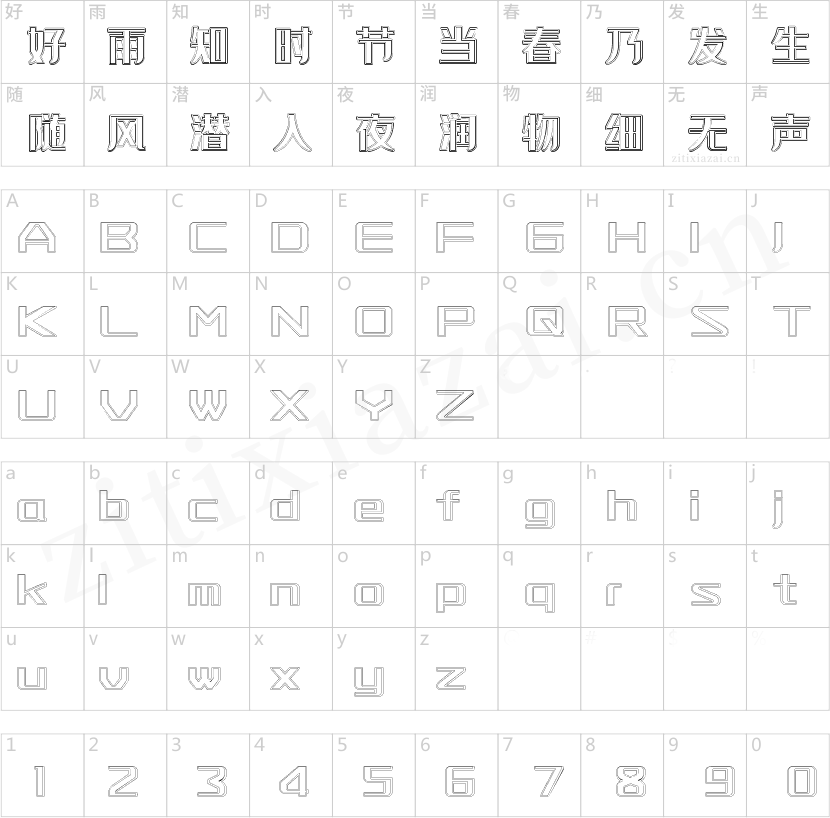
字小魂空心雅黑字魂44号-空心雅黑,这款字体结构工整、笔画清晰,兼顾美观与易读性,适用于标题、正文、海报、包装、LOGO 等多种场景。字形优雅稳定,风格百搭耐看,适配日常排版与创意设计,让文字呈现更舒适、更具质感。字小魂空心雅黑字魂44号-空心雅黑一笔一画,皆是细节,以均衡的比例、流畅的线条打造舒适视觉体验,字形端正大气,风格简约现代。无论是商业设计、品牌宣传还是日常排版,都能轻松驾驭,让文字更有格调与力量。字小魂空心雅黑字魂44号-空心雅黑字体下载。
字小魂空心雅黑字体设计说明
字魂字体字小魂空心雅黑字体是由字魂创意字库设计并生产的一款可商用的字体,被收录于字小魂系列。该字体支持GB-2312标准,包含6912个中文、字母、符号和数字,字体类型偏向黑体,具有可爱、简约、时尚的风格,在市面上广泛用于包装印刷、招聘、广告等场景。